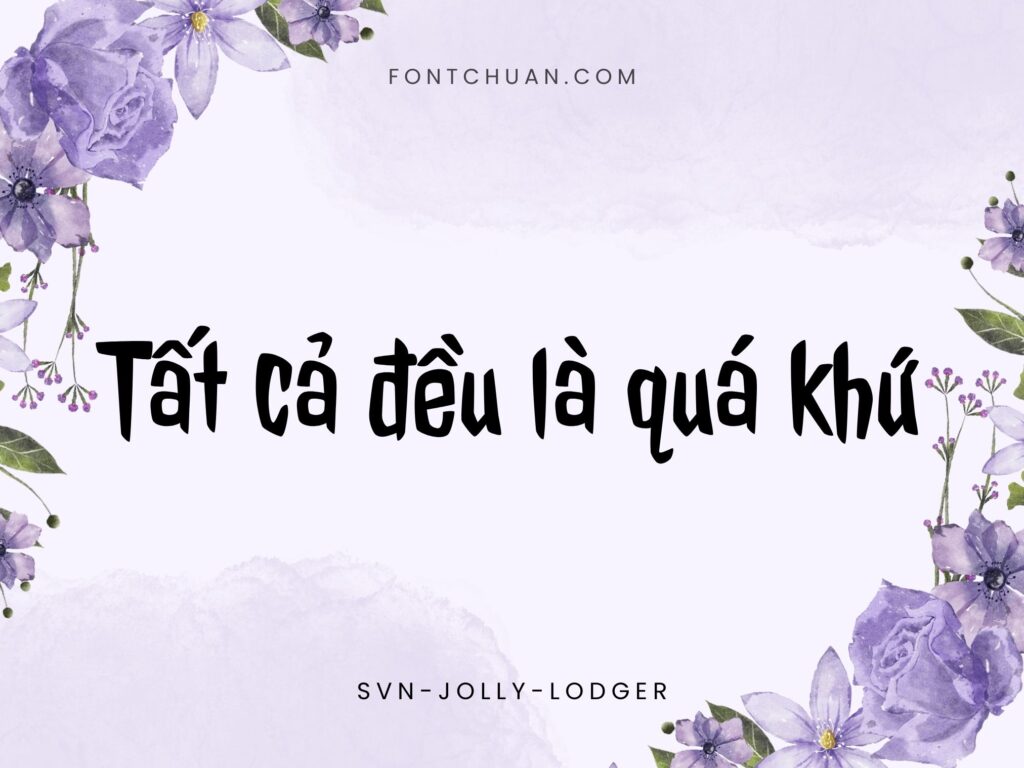
Font SVN Jolly Lodger Việt Hóa
Tác giả Font: Stuart Sandler
Font SVN Jolly Lodger là phiên bản Việt hóa của kiểu chữ Jolly Lodger, được thực hiện bởi STYLEno.1 Fonts. Jolly Lodger là một kiểu chữ hiển thị với thiết kế vui nhộn và độc đáo, mang phong cách hoạt hình, hơi hướng retro, và có một số biến thể Font Gothic trong các ký tự để tạo điểm nhấn mạnh mẽ và sắc nét. Các ký tự được thiết kế với đường nét không đồng đều, tạo cảm giác thủ công và thân thiện. Font này bao gồm các ký tự chữ hoa, chữ số và dấu câu, hỗ trợ đa ngôn ngữ. Với thiết kế đặc trưng, Jolly Lodger phù hợp cho nhiều mục đích sử dụng như thiết kế tiêu đề, logo, poster, bao bì sản phẩm và các ấn phẩm truyền thông.
SVN Jolly Lodger lý tưởng cho các dự án thiết kế yêu cầu sự vui nhộn và độc đáo, như thiết kế tiêu đề, logo thương hiệu và các ấn phẩm truyền thông. Các ngành nghề như quảng cáo, giáo dục và ẩm thực có thể tận dụng font này để tạo điểm nhấn trong thiết kế. Ngoài ra, font cũng thích hợp cho các sự kiện như Halloween, Giáng sinh, Tết và các lễ hội khác.